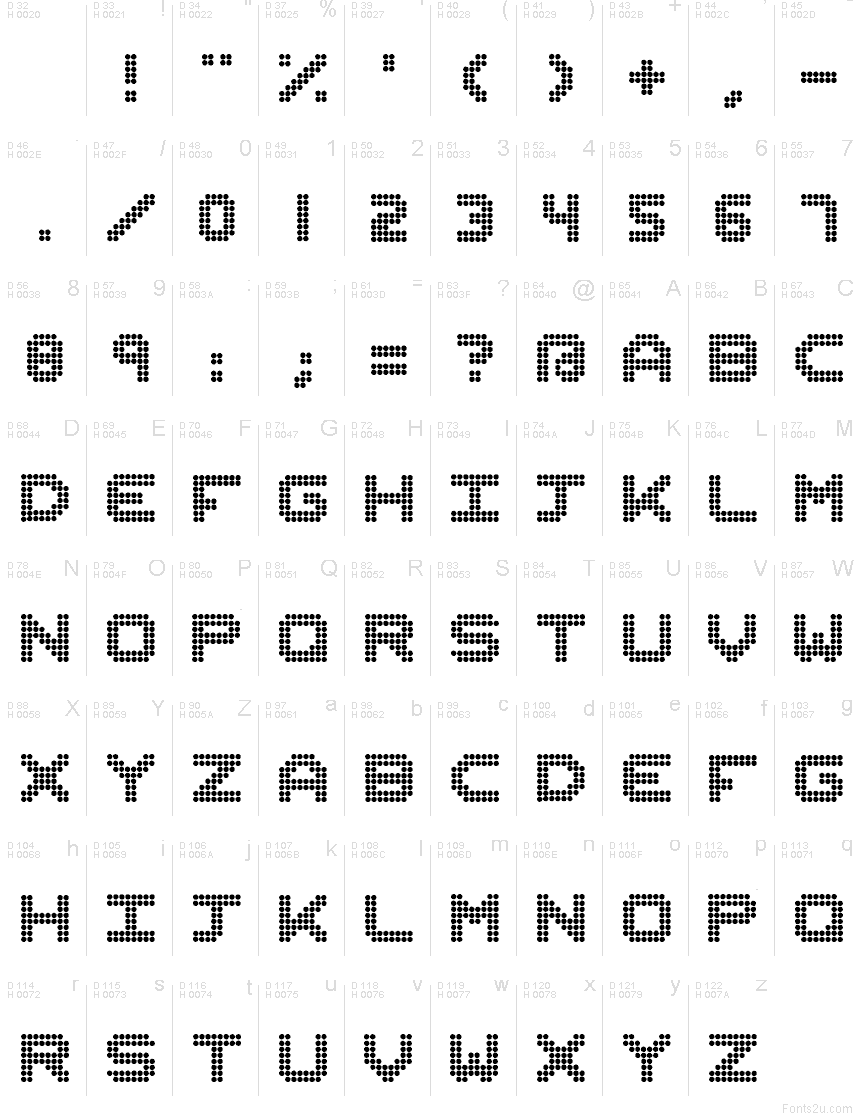
Dotfont je bezplatný font typu dot-matrix s čistým retro-digitálním nádechem. Písmena jsou sestavena z rovnoměrně rozmístěných kruhových bodů, což velkým písmenům dodává rytmus „low-tech“ obrazovky, zatímco tvary zůstávají široké, jednoduché a nezaměnitelně geometrické.
Přirozeně zapadne do titulků na plakátech, brandingu v arkádovém stylu, přebalů alb, úvodních titulků a grafiky událostí, kde může bezplatné písmo využít estetiku rané počítačové éry, aniž by působilo příliš složitě. Protože každé písmeno dodržuje stejnou tečkovanou logiku, dobře funguje i pro krátké popisky, monogramy a výrazné titulky na obálkách, které vyžadují strohý pixelový signál.
Dotfont